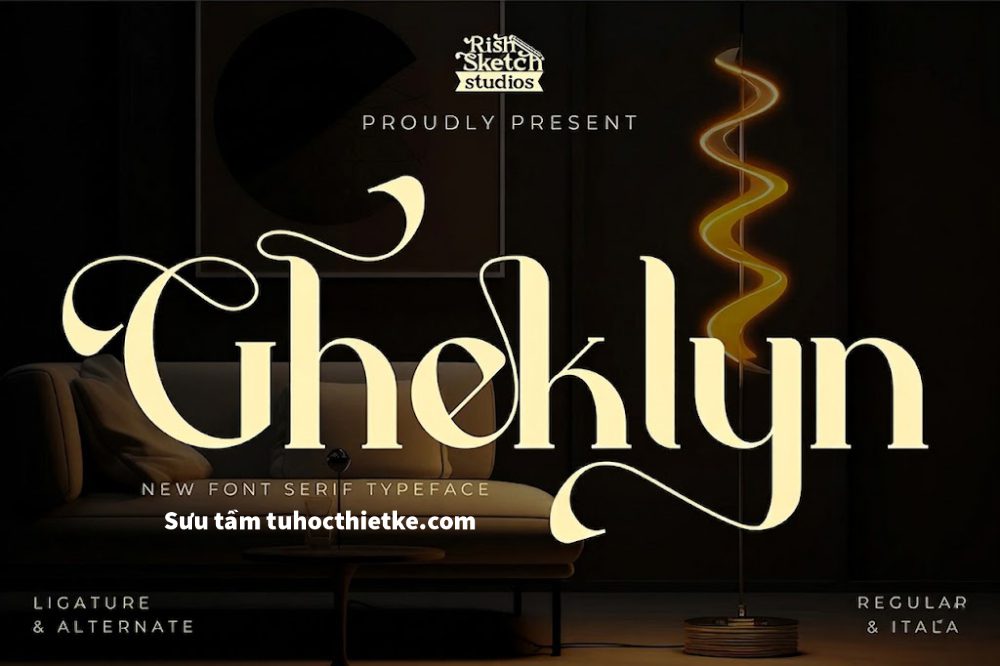
Trong thiết kế đồ họa, font chữ không chỉ đơn giản là phương tiện hiển thị nội dung mà còn là yếu tố quan trọng quyết định cảm xúc, phong cách và mức độ chuyên nghiệp của một sản phẩm. Một thiết kế có hình ảnh đẹp nhưng sử dụng font chữ không phù hợp vẫn có thể khiến tổng thể trở nên thiếu cân đối, khó đọc hoặc kém thu hút. Vì vậy, việc lựa chọn và Tải Font Chữ phù hợp luôn là bước quan trọng đối với designer, marketer, content creator và những ai thường xuyên làm việc với hình ảnh.
Hiện nay, có rất nhiều bộ font miễn phí được chia sẻ trên internet với đa dạng phong cách như hiện đại, tối giản, cổ điển, nghệ thuật, viết tay, sans serif, serif, display hoặc font trang trí. Những font chữ này có thể ứng dụng trong nhiều dự án thiết kế khác nhau như poster, banner, logo, brochure, thumbnail YouTube, bài đăng mạng xã hội, bao bì sản phẩm, profile công ty hay các ấn phẩm truyền thông thương hiệu.
Vì Sao Font Chữ Quan Trọng Trong Thiết Kế?
Font chữ là một trong những yếu tố đầu tiên người xem cảm nhận khi nhìn vào thiết kế. Mỗi kiểu chữ đều mang một cá tính riêng. Font sans serif thường tạo cảm giác hiện đại, rõ ràng và tối giản. Font serif mang đến sự sang trọng, cổ điển và đáng tin cậy. Font script tạo cảm giác mềm mại, nghệ thuật và cá nhân hóa. Trong khi đó, font display lại phù hợp với các thiết kế cần sự nổi bật, sáng tạo và khác biệt.
Một font chữ phù hợp có thể giúp thông điệp trở nên rõ ràng hơn, đồng thời tăng khả năng ghi nhớ thương hiệu. Ngược lại, nếu chọn sai font, thiết kế có thể bị rối mắt, khó đọc hoặc không truyền tải đúng tinh thần của nội dung. Đây là lý do designer luôn cần xây dựng cho mình một thư viện font chất lượng để sử dụng linh hoạt trong từng dự án.
Đa Dạng Phong Cách Thiết Kế
Khi Tải Font Chữ miễn phí từ các nguồn uy tín, bạn có thể mở rộng kho tài nguyên cá nhân với nhiều phong cách khác nhau. Mỗi dự án thiết kế sẽ cần một kiểu chữ riêng để phù hợp với đối tượng người xem và mục tiêu truyền tải. Ví dụ, thiết kế poster âm nhạc có thể cần font mạnh mẽ, cá tính; thiết kế thương hiệu mỹ phẩm lại phù hợp với font thanh lịch, mềm mại; còn thiết kế công nghệ thường ưu tiên font hiện đại, gọn gàng.
Tăng Tốc Quy Trình Làm Việc
Việc có sẵn một thư viện font phong phú giúp designer tiết kiệm nhiều thời gian trong quá trình lên ý tưởng. Thay vì phải tìm kiếm font mới cho từng dự án, bạn có thể nhanh chóng chọn ra những font phù hợp từ bộ sưu tập đã lưu trữ. Điều này đặc biệt hữu ích khi cần xử lý nhiều thiết kế trong thời gian ngắn như bài đăng mạng xã hội, banner quảng cáo hoặc thumbnail video.
Các Nhóm Font Chữ Phổ Biến Trong Thiết Kế
Font Sans Serif
Sans serif là nhóm font không có chân, thường mang phong cách hiện đại, tối giản và dễ đọc. Đây là lựa chọn phổ biến trong thiết kế website, app, banner, poster, slide thuyết trình và nhận diện thương hiệu. Những font sans serif thường giúp bố cục trở nên sạch sẽ, chuyên nghiệp và phù hợp với các thương hiệu trẻ trung, công nghệ hoặc sáng tạo.
Font Serif
Serif là nhóm font có chân, thường tạo cảm giác cổ điển, trang trọng và đáng tin cậy. Font serif rất phù hợp với thiết kế tạp chí, sách, thương hiệu cao cấp, lĩnh vực giáo dục, thời trang hoặc các ấn phẩm cần sự tinh tế. Khi sử dụng đúng cách, font serif có thể giúp thiết kế trở nên sang trọng và có chiều sâu hơn.
Font Script
Font script mô phỏng nét chữ viết tay, thường mang lại cảm giác mềm mại, nghệ thuật và gần gũi. Loại font này phù hợp với thiệp mời, logo cá nhân, thiết kế mỹ phẩm, thời trang, wedding, handmade hoặc các sản phẩm cần sự nhẹ nhàng, cảm xúc. Tuy nhiên, designer nên sử dụng font script với liều lượng hợp lý để tránh gây khó đọc.
Font Display
Font display là nhóm font trang trí, thường có hình dáng độc đáo, mạnh mẽ và nổi bật. Đây là lựa chọn lý tưởng cho tiêu đề poster, banner sự kiện, thumbnail, bìa album, thiết kế game hoặc các sản phẩm cần thu hút ánh nhìn nhanh. Vì có tính biểu cảm cao, font display thường nên được dùng cho tiêu đề lớn thay vì đoạn văn dài.
Cách Chọn Font Chữ Phù Hợp Cho Dự Án
Xác Định Mục Đích Thiết Kế
Trước khi chọn font, bạn cần hiểu rõ mục tiêu của dự án. Thiết kế dành cho thương hiệu cao cấp sẽ khác với thiết kế cho sự kiện âm nhạc, sản phẩm công nghệ hay bài đăng bán hàng. Khi xác định được phong cách tổng thể, bạn sẽ dễ dàng chọn font chữ phù hợp hơn.
Ưu Tiên Khả Năng Đọc
Một font chữ đẹp nhưng khó đọc sẽ không mang lại hiệu quả tốt trong thiết kế. Đặc biệt với các nội dung quan trọng như tiêu đề, thông tin sản phẩm, giá bán, lời kêu gọi hành động hoặc nội dung quảng cáo, khả năng đọc luôn phải được ưu tiên. Hãy kiểm tra font ở nhiều kích thước khác nhau để đảm bảo chữ vẫn rõ ràng trên cả màn hình lớn và thiết bị di động.